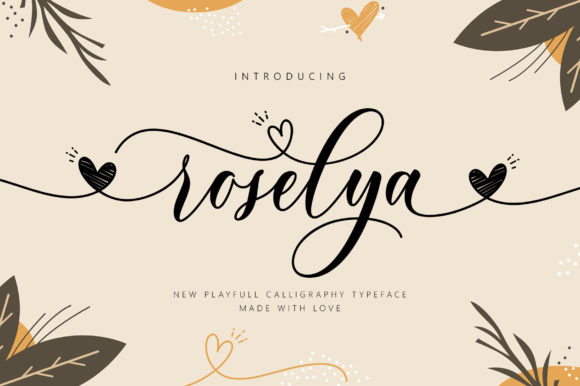
Roselya Script Font
Якщо ви шукаєте високоякісні ресурси, такі як Roselya Script Font, цей преміум-пакет є фантастичним вибором для ваших творчих проектів.
Створений з високою точністю, Roselya Script Font забезпечує чисті вектори, плавну типографіку та комерційну ліцензію для вашого спокою.
Незалежно від того, чи створюєте ви продукти POD (друк на вимогу), весільні запрошення або графіку для соціальних мереж, Roselya Script Font стане ідеальним вибором.